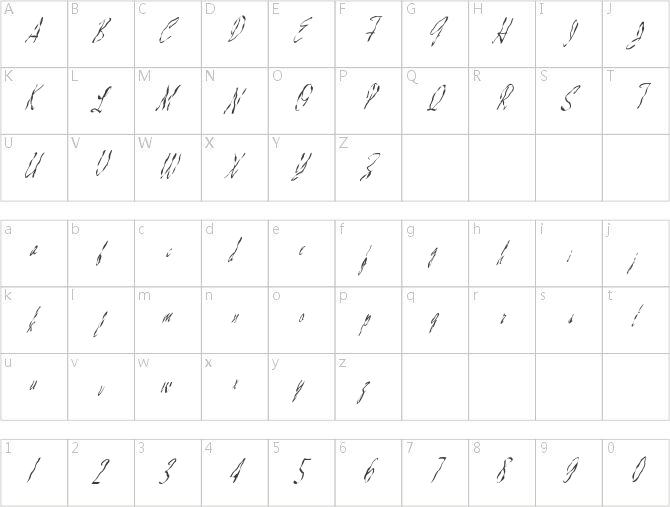
FZ HAND 13 WAVEY ITALIC
FZ HAND 13 WAVEY ITALIC介绍
FZ HAND 13 WAVEY ITALIC字体字库是一款让人赏心悦目、百看不厌的英文字体,适合各类广告和产品包装设计应用,字体大小0.06MB,格式为ttf字体,上传用户是洛洛,作者/版权方为未知